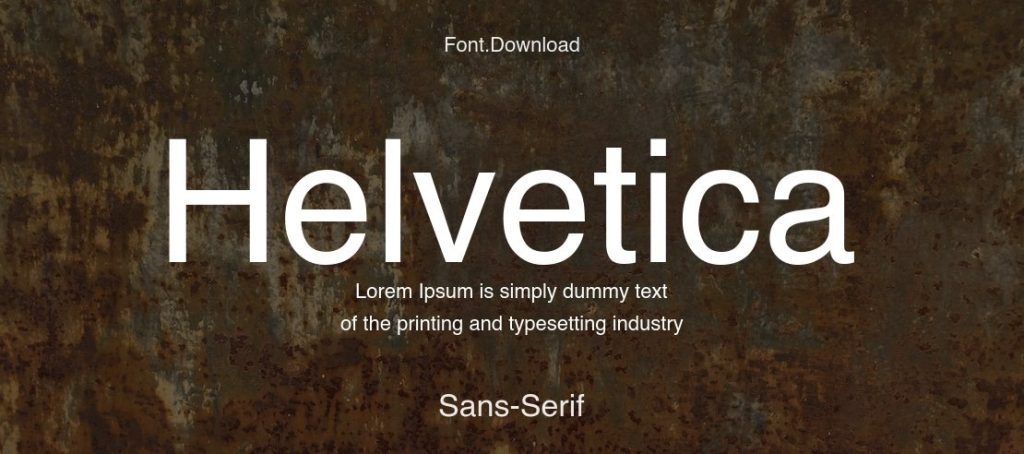
Tác giả: Max Miedinger
Ngày phát hành: 1957
Ngôn ngữ: Tiếng Anh, Tiếng Việt
Bộ Font: Font Helvetica
Phân loại: Hiện đại
Font Helvetica là biểu tượng của sự tinh tế và hiện đại trong thiết kế chữ. Kiểu chữ này thuộc bộ font chữ không chân được biết đến với kiểu dáng đơn giản, dễ đọc. Font Helvetica đã trở thành lựa chọn hàng đầu của nhiều nhà thiết kế và thương hiệu toàn cầu khi muốn truyền tải thông điệp một cách rõ ràng và chuyên nghiệp. Sự cân đối giữa các nét chữ và không gian trong Font Helvetica tạo nên một cảm giác hài hòa, khiến nó phù hợp với mọi loại ấn phẩm từ in ấn. Với các nét chữ sắc sảo, cân đối và tối giản, font chữ thể hiện sự thanh lịch, rõ ràng và dễ đọc, khiến nó trở thành lựa chọn ưu tiên cho các thiết kế cần sự chuyên nghiệp và tính ứng dụng cao.